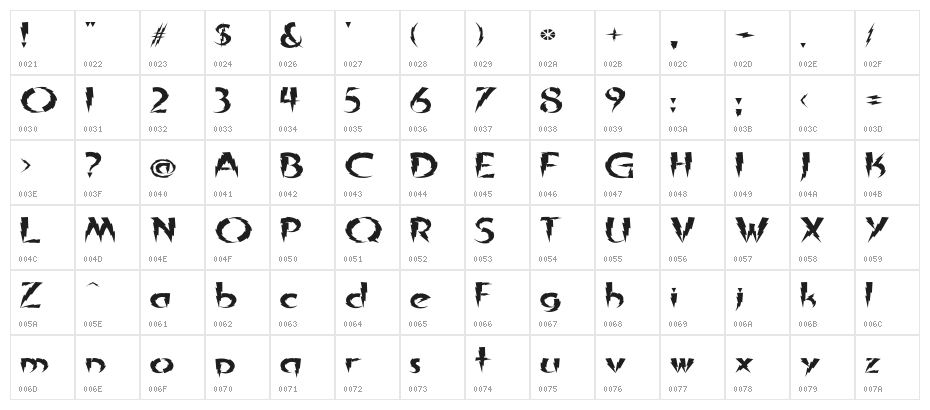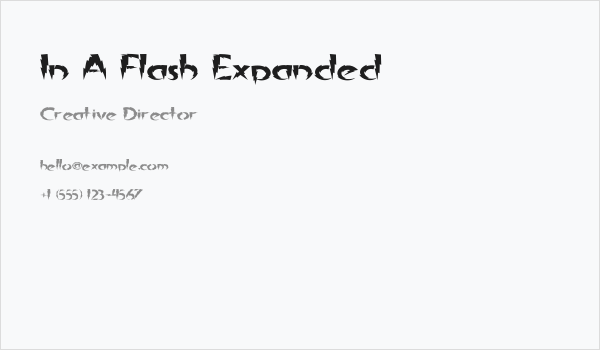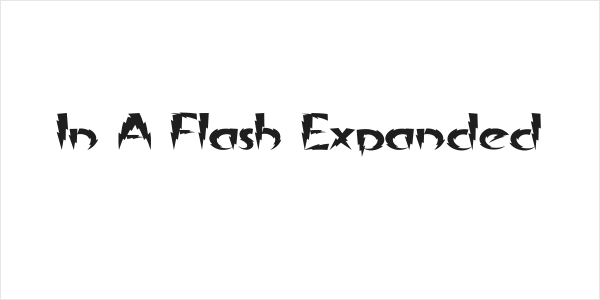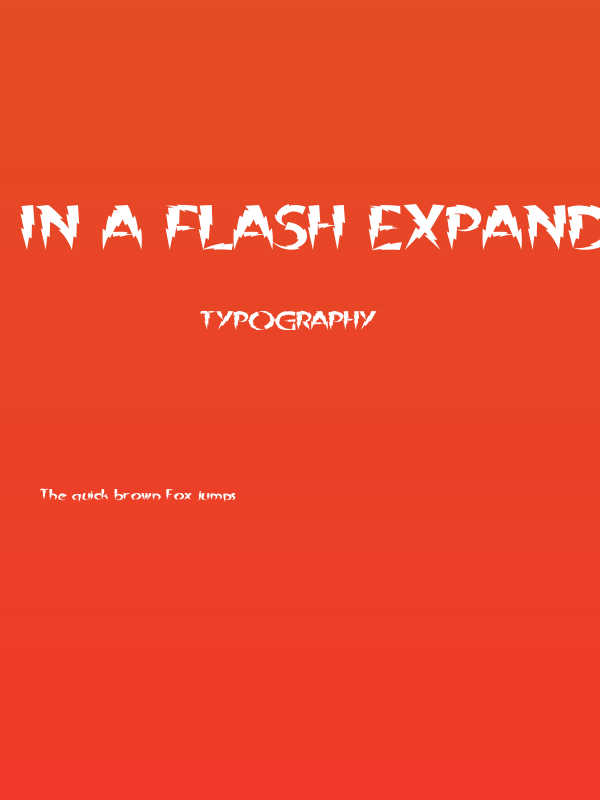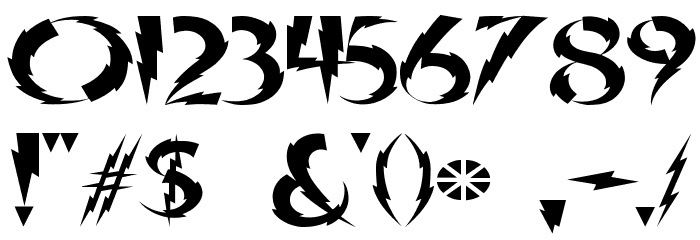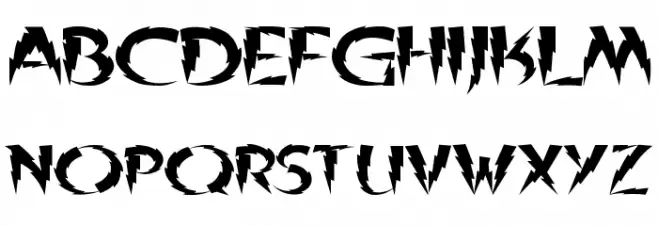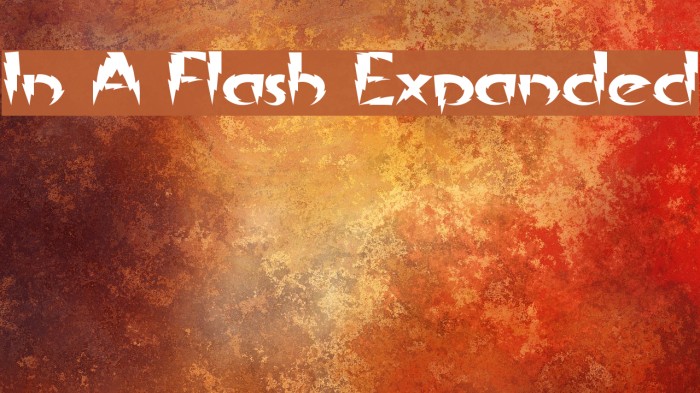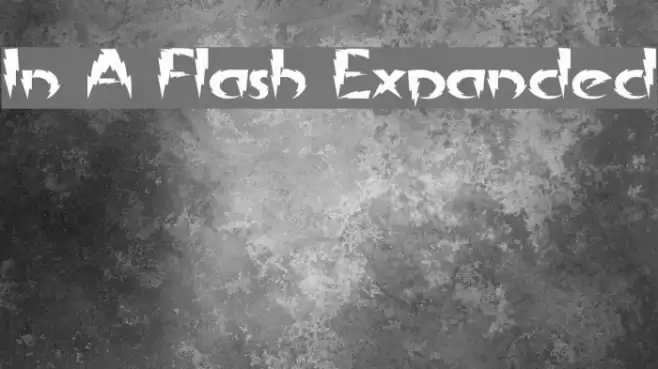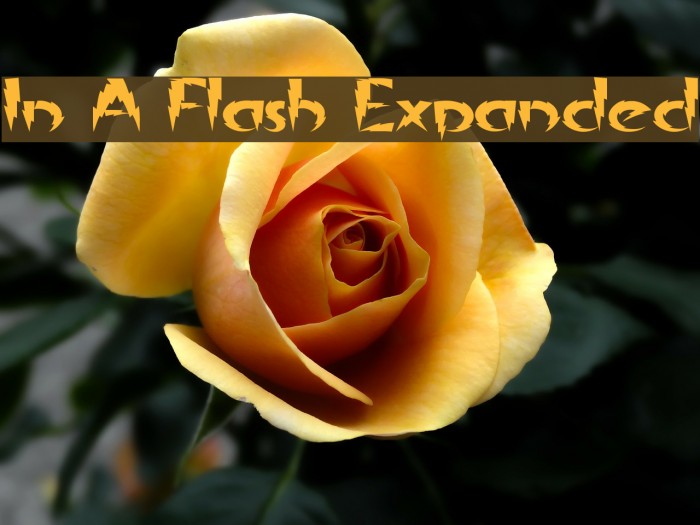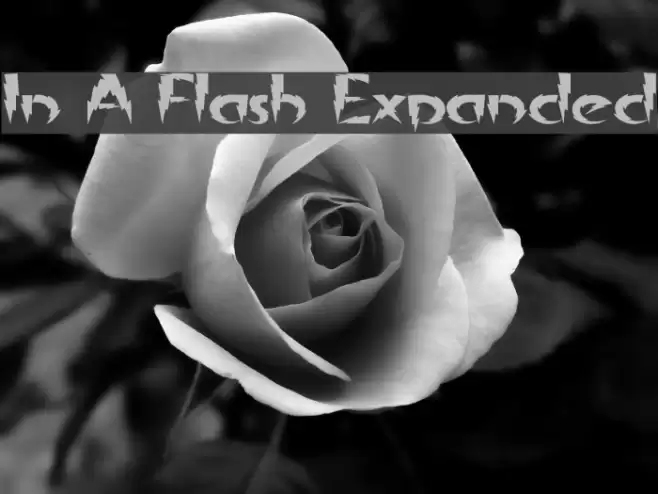
In A Flash Expanded Font
IN-A-FLASH-EXPANDED 大文字
IN-A-FLASH-EXPANDED 小文字
IN-A-FLASH-EXPANDED その他の文字
| ウェイト | Expanded |
| おすすめプロジェクト | Ideal for posters, album covers, branding, and any project needing a bold, energetic look. |